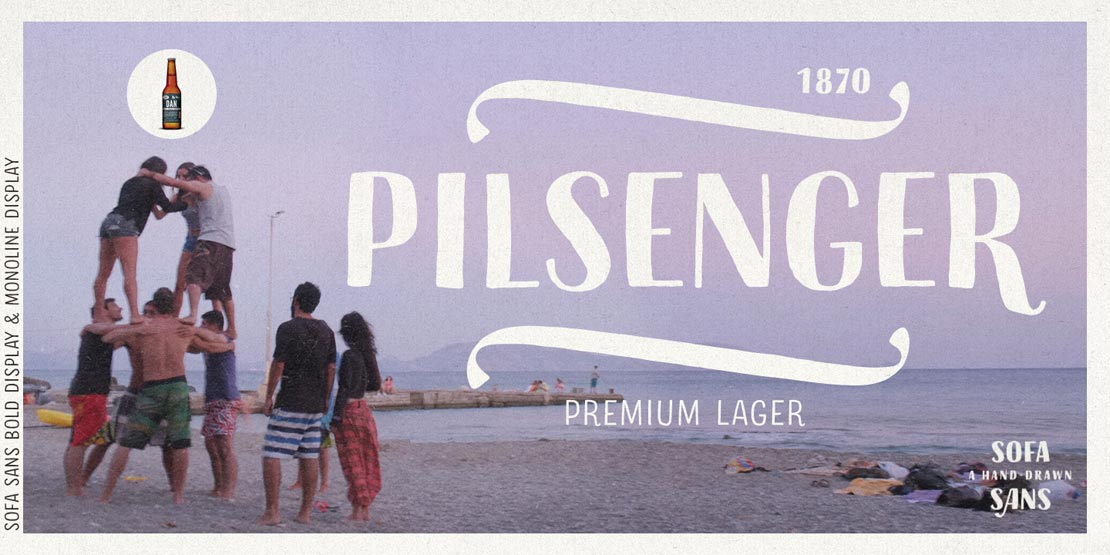
Handgezeichnete »Sofa Sans«
Georg Herold-Wildfellner hat eine neue Schriftfamilie gestaltet. »Sofa Sans« bietet 18 dekorative Fonts, zwei optische Größen und über 1.000 Glyphen pro Schnitt für entspannte Gestaltungsideen.
Ziel des Wiener Type-Designers war es, eine warme, freundliche und kräftige Schriftfamilie zu entwickeln. Die handgezeichneten Zeichen unterstreichen den sympathischen Charakter der »Sofa Sans« und bieten Raum zum Variieren. Zusätzliche dekorative Schnitte erweitern das Erscheinungsbild der Sans-Serif.
Viel Wert wurde auf Detailarbeit gelegt. Der Buchstabe »R« liegt z.B. für jeden Schnitt in acht verschiedenen Varianten vor: ein Standard-R, ein R für kontextuelle Ersetzungen, ein Schwungschrift-R sowie ein Titelvarianten-R mit 5 unterschiedlichen Beinlängen, das sich von selbst dem verfügbaren Weißraum anpasst.
»Sofa Sans« macht außerdem ausgiebig Gebrauch von weiteren OpenType Features – darunter unter anderem kontextbedingte Varianten, Schwung- und Titelschriftvarianten, Initial- und Finalformen, Stylistic-Sets, bedingte Ligaturen und mehr.
Die Familie bietet vier Schrift-Stärken von einer monolinearen »Light« bis zur kontrastreichen »Black«. Für einen breiten und flexiblen Einsatz gibt es zwei optische Größen: Standard und Display mit maximalem Kontrast speziell in der Bold und der Black. Zusätzliche Schatten-, 3D-, Inline- und schraffierte Schnitte ergänzen das Paket. Die Effekt-Schnitte gibt es auch als Layer-Fonts zur zweifärbigen Gestaltung.